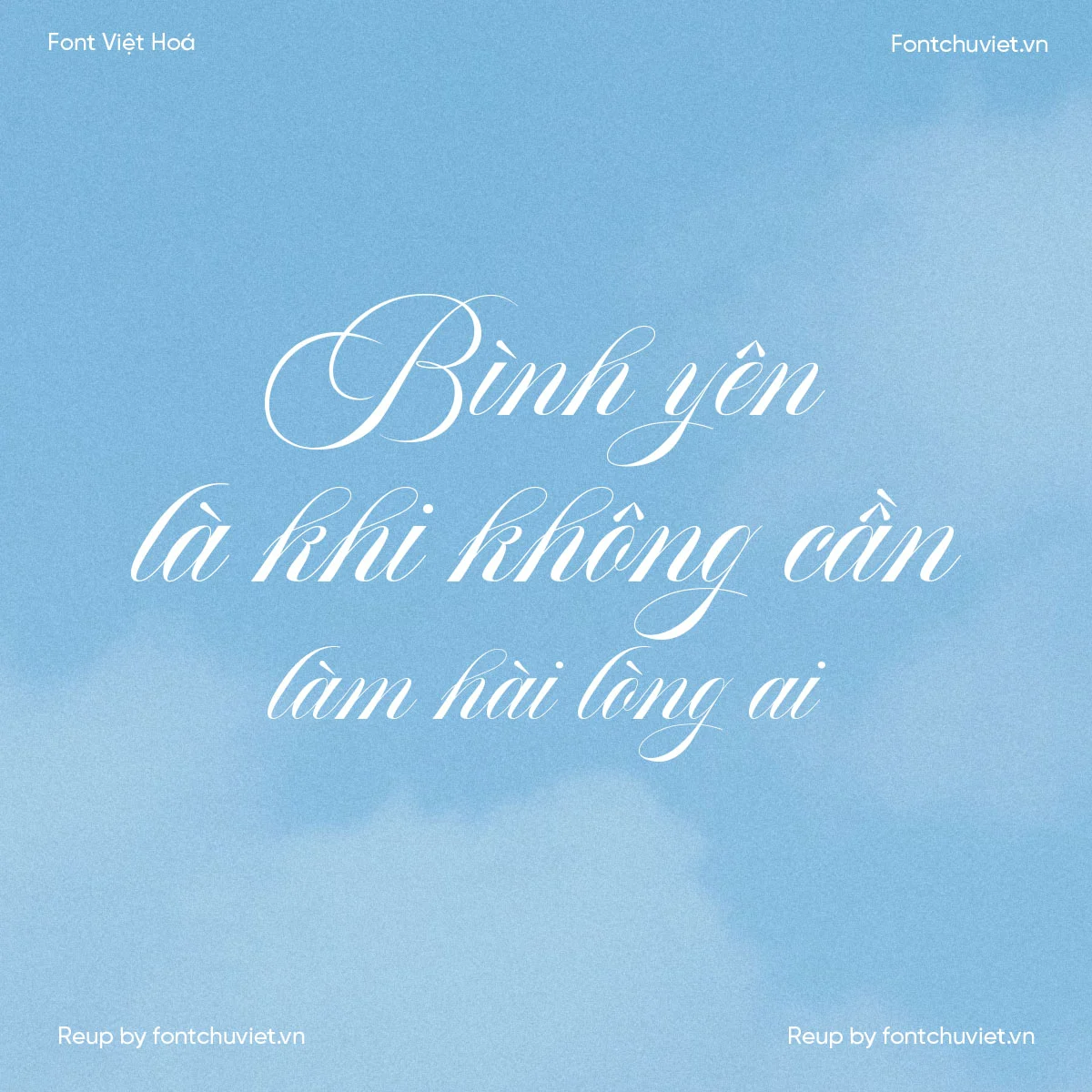
Font VL Aston Script – Font Việt hoá
Cỡ chữ: 60px Aa aa AA Thử font Việt hoá 1234567890 0/300 Gõ văn bản bên dưới để xem trước font chữ ◪ View Glyphs Font VL Aston Script – Font Việt hoá là một trong những font viết tay đẹp và phổ biến hiện nay. Với nét đậm và đẹp, font này là lựa … Đọc tiếp Font VL Aston Script – Font Việt hoá